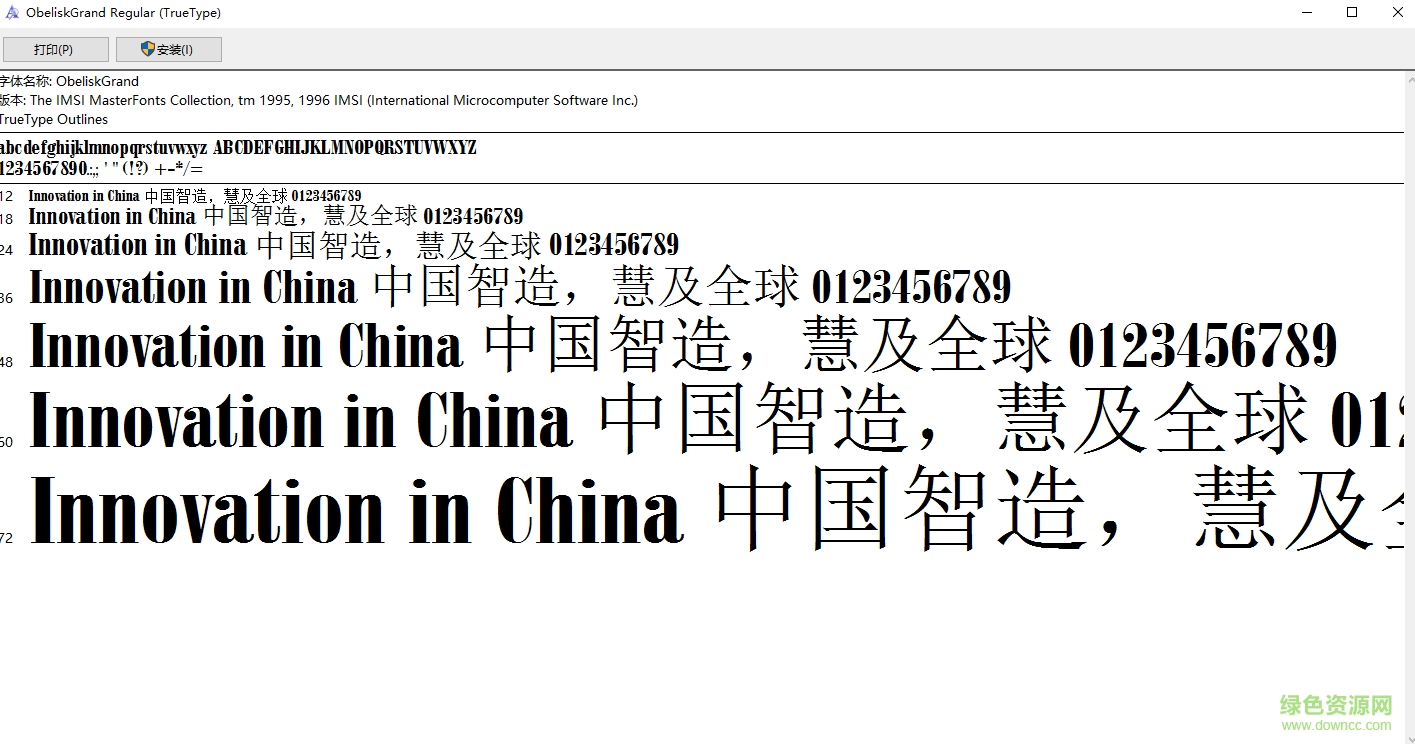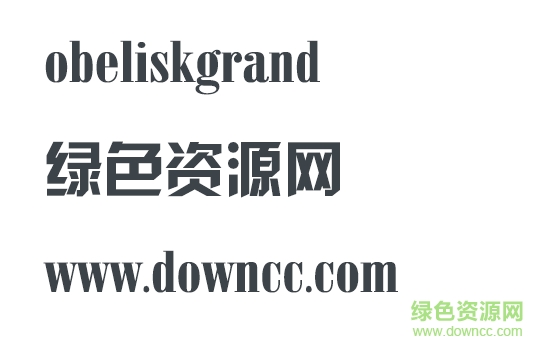
obeliskgrand
obeliskgrand字體介紹
流暢美觀,線條明快
obeliskgrand字體
obeliskgrand測(cè)評(píng)
一款非常實(shí)用中文簡(jiǎn)體字體,該字體線條粗細(xì)適中,字形端正大方得體,整體風(fēng)格非常的出色,可用于藝術(shù)設(shè)計(jì)、包裝印刷、簽名設(shè)計(jì)、圖形設(shè)計(jì)等領(lǐng)域